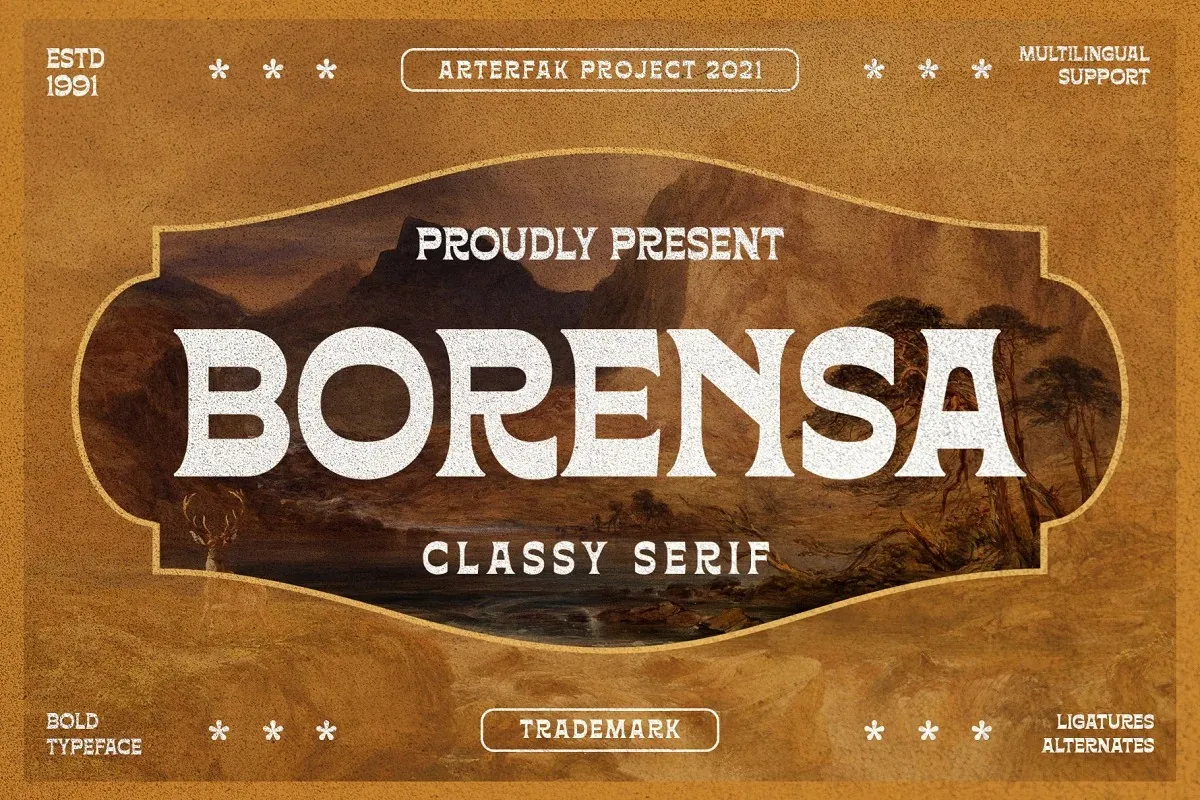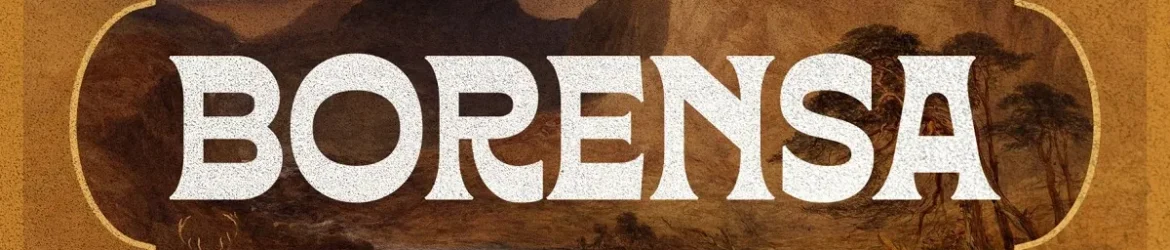
Borensa é uma fonte Display criada pelo Arterfak Project que captura a elegância vintage dos anos 60. Inspirada nos livros históricos e nas marcas antiguinhas, essa fonte robusta e vintage revive esse sentimento nostálgico. Borensa traz uma elegância clássica adequada para desenhos formais, tornando-a perfeita tanto para o texto principal quanto para headlines longos. Seja você um criador de design ou designer gráfico profissional, este fonte é uma excelente escolha para aprimorar seus projetos com um toque vintage e sofisticado. Em qualquer projeto que precise de um estilo moderno e elegante, Borensa estará sempre à mão.